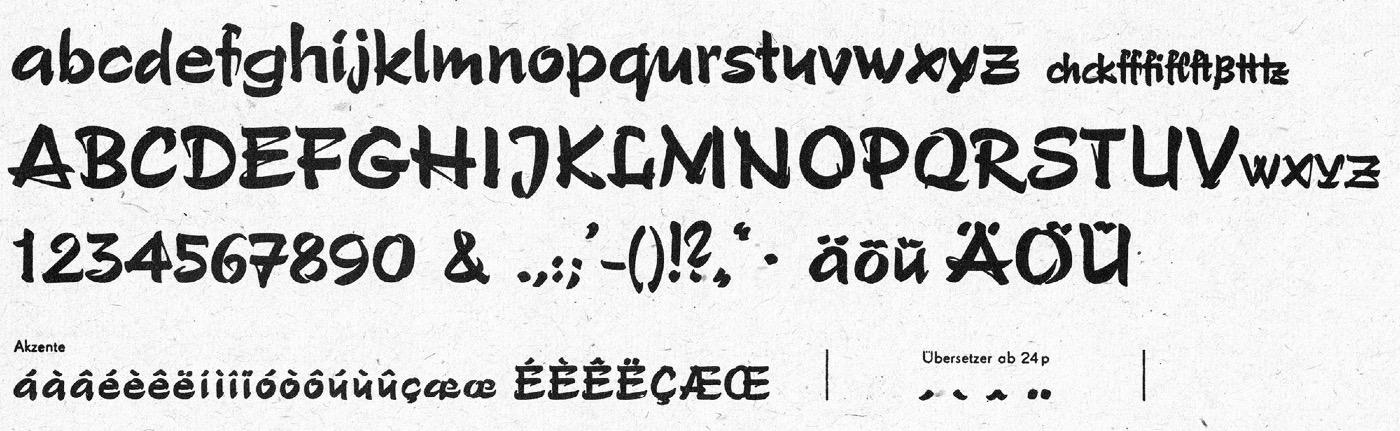
Font-Wiki: Polo (Typoart)
Die Pinselschrift Polo wurde um 1960 von Carl Rudolph Pohl für Typoart geschaffen. Digitalisierungen der Schrift gibt es unter dem Originalnamen von Profonts sowie als Paola von »astype«. Beide Versionen sind mit über 500 Glyphen recht gut ausgebaut.
Original-Bleisatzmuster von Typoart
Die Profonts-Digitalisierung
Bleisatzmuster